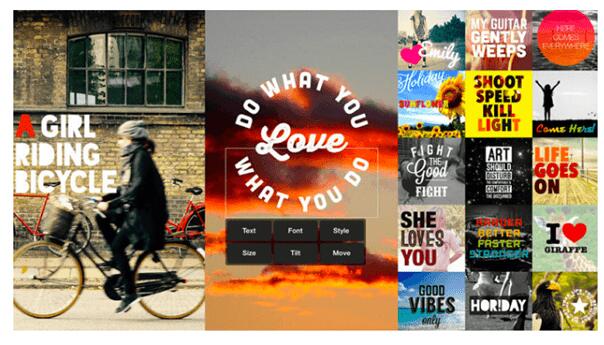
Чтобы обратить на себя внимание, блогерам Instagram нужно придумывать интересный текст, делать качественные фото и постить завораживающие сториз. Но есть ещё один способ привлечь внимание подписчиков и выделиться среди других блогеров. Иногда достаточно изменить шрифт в Инстаграме, и страница будет бросаться в глаза.
Например, вы можете сделать красивое оформление шапки профиля или, как вариант, написать необычными буквами в истории или постах. В статье ниже поговорим как это сделать на смартфонах или компьютерах.
Как поменять шрифт в Instagram на другой
Инстаграм системно смену шрифтов не предусматривает, но это легко сделать при помощи:
- приложений;
- веб-сайтов;
- юникода — специальных символов, уже добавленных во все операционные системы.
Рассмотрим подробнее все варианты.
Веб-сайты для смены шрифтов Инстаграме
Для тех, кто не хочет скачивать и инсталлировать программы на свой телефон, можно менять текст онлайн. Достаточно скопировать нужные цифры и буквы на сайт, а затем вставить в Инстаграм. Платформы отличаются большим выбором стилей: готический, рукописный, печатный, модный, каллиграфический и другие. Просто выделяйте ссылку, копируйте её и открывайте в новом окне. Вот список онлайн-сервисов:
- megacooltext.com — самый навороченный из всех генераторов. Делает разные варианты красивых шрифтов для Инстаграма, предлагает свои. Единственный минус — иногда может предложить не то, чего вы ждёте
- textgenerator.ru — просто выбираем подходящий шрифт, вставляем в него свой текст и, вуаля, система все перепечатывает буквально за секунды;
- lingojam.com/FontsForInstagram — здесь наоборот, мы вводим текст, а система автоматически меняет его на автоматически подобранные шрифты. Удобно, но не очень;
- textygram.ru — много классных вариантов, но работает только с английским языком;
- qaz.wtf — явно сделанный программистами сайт, в котором буквы меняются через строку. Зато удобно — показаны названия разных эффектов, вот только надо ли? 🙂
Как меняют шрифт при помощи UNICODE
Юникод — это способ кодирования, при помощи которого можно написать знаки всех языков мира и применить иконки, вроде таких стрелочек ← → и кружочков •. Немного усложнённый вариант, но зато можно подобрать именно то, что хочется. Есть небольшой недочёт – копируется каждая буква отдельно по очереди. Нужно найти в таблице необходимый символ, скопировать его и вставить в какой-нибудь текстовый редактор.
Таблица символов Unicode
Вот как можно вызвать таблицу символов для Windows и для MacOS.
Способы для Windows
1) Быстрый — нажимаем клавишу Windows или выбираем меню Пуск, начинаем набирать текст «Симв» или «Таблица симв», а система уже подскажет подходящее приложение.
2) Надёжный — Пуск → Программы → Стандартные → Служебные → Таблица символов.
Способы для MacOS
Выбираем место, куда будем добавлять специальный символ — текстовый документ, поле ввода в Whatsapp или Телеграм или любое другое место. Ведём мышку к верхнему окну, нажимаем Правка → Специальные символы.
Дальше просто копируем и вставляем нужные символы — это просто 🙂
Приложения и программы смены шрифта в Инсте
Если вам нужно не просто сделать красивые шрифты в профиле, а еще и добавить их на изображения вашего аккаунта, то можно воспользоваться этими приложениями. Это просто — скачиваем, обрабатываем фотографии и пользуемся приложенными.
Программы на платформе Android в Play Market:
- Cool Fonts for Instagram Bio — отличается простым и удобным интерфейсом, а также возможностью сразу писать выбранными шрифтами. Поддерживает различные стили: от печатных до каллиграфических. Также на выбор большой выбор эмодзи и смайликов.
- Font for Instagram — много разных любопытный смайликов и шрифтов.
- Font for Instagram-Beauty Font Style — при помощи него можно не только менять стили написания букв, но и сделать надпись цветной. Есть функция предварительного просмотра, что облегчает подбор.
- Typography Master — позволяет редактировать не только текст, но и фото. Содержит большую коллекцию модных шрифтов: рукописные, готические, кириллица, латиница.
Typography Master — программа для смены шрифтов в Инсте
Программы по изменению шрифтов в Instagram для эппловской iOS, которые доступны в AppStore:
-
Font Candy— отличается небольшим выбором, но это компенсируется красивым художественным оформлением. Текст можно менять, смешивая, наклоняя или вырезая шрифты, а еще размещая символы на фоне изображения.
Font Candy — программа для смены шрифтов в Инсте
- Better Font — популярное приложение среди поклонников iPhone. Оно распространяется бесплатно и не содержит рекламы. Но, чтобы воспользоваться дополнительной библиотекой, нужно немного заплатить.
- Symbolizer Fonts — позволяет интегрировать шрифты на своё устройство и сразу публиковать красивые надписи или тексты в соцсети.
- Cool Fonts — работает как и предыдущее приложение. Позволяет написать курсивом, жирным, сделать подчёркнутый текст или зачёркнутые буквы.
- Typorama — приложение с простым интерфейсом и большим количеством прикольных функций. Имеются стоковые изображения и коллекции цитат, которые подходят к этим изображениям. Самому нужно выбрать тематику картинки и соответствующий текст. Есть возможность использовать свое фото. Сервис подходит всем, кто любит постить картинки с мотивашками.
Приложение Typorama автоматически создаёт сложный текстовый макет
- Fonts for Instagram — позволяет набирать текст прямо в приложении, а оттуда копировать и вставлять в Инстаграм. Здесь очень большая коллекция разнообразных шрифтов, так что выбрать есть из чего.
- Шрифты & текст смайликов for Инстаграм — широкий ассортимент оригинальных вариантов для написания букв, а также смайликов. Нужно подобрать понравившийся стиль и набрать текст, дополнив его смайликами по необходимости.
- Stylish Text — еще одна довольно популярная прога для выбора стиля написания букв латиницей.
Среди приложений, представленных и для Android, и для iOS:
- Word Swag — содержит массу шаблонов, изображений, фонов и шрифтов. Позволяет изменять величину и наклон символов, использовать сразу несколько стилей текста и делать его цветным .
Word Swag для iOS и Android с большим количеством функций
- Phonto — программа, радующая широким выбором стикеров и шрифтов. Если использовать трафаретные символы, то можно добиться эффекта аппликации, сделать эффектные подписи. Имеется расширенная платная версия.
Phonto — удобное приложение с большим ассортиментом стикеров и шрифтов
- Canva — отличается широким ассортиментом стилей написания текста на любой вкус. Их можно увеличивать/уменьшать, изменять угол наклона, цветовую гамму, форму и месторасположение.
Онлайн – редактор Canva
Красивые оригинальные шрифты — это не только способ украсить и выделить профиль в Instagram, но и возможность более быстрого продвижения блога. Только учтите, что слишком много смайликов и разнообразных шрифтов могут оттолкнуть подписчиков.